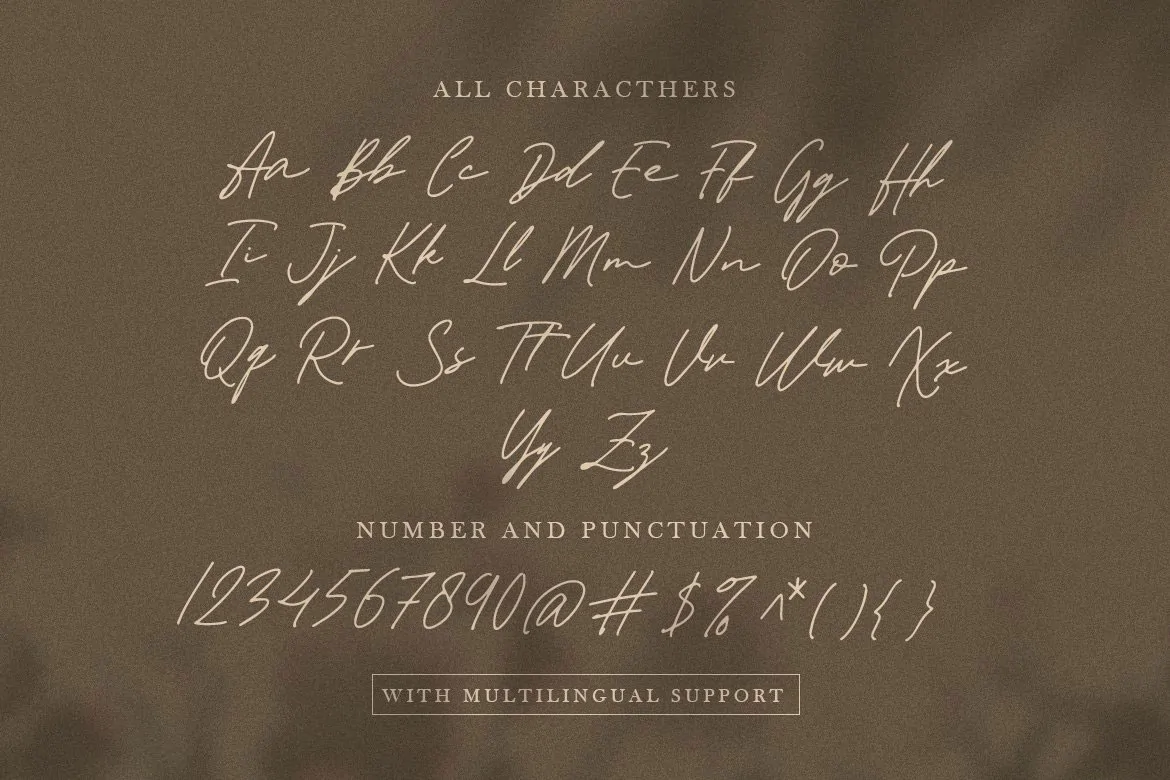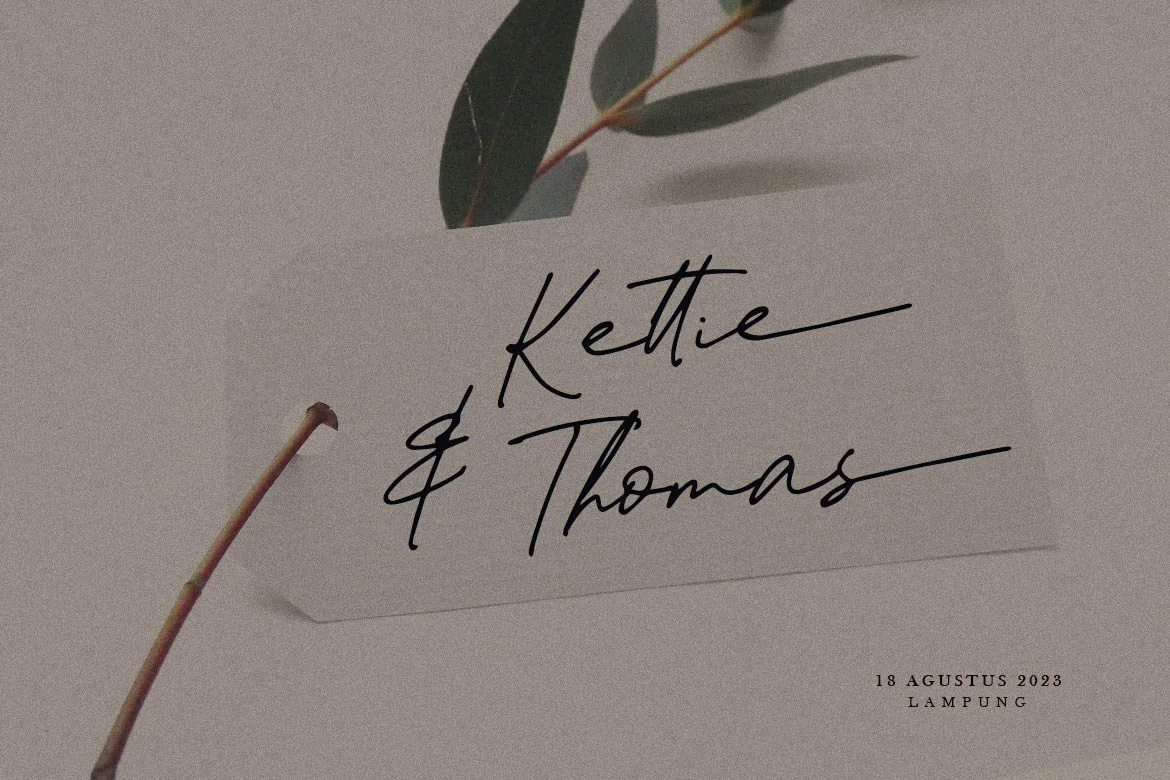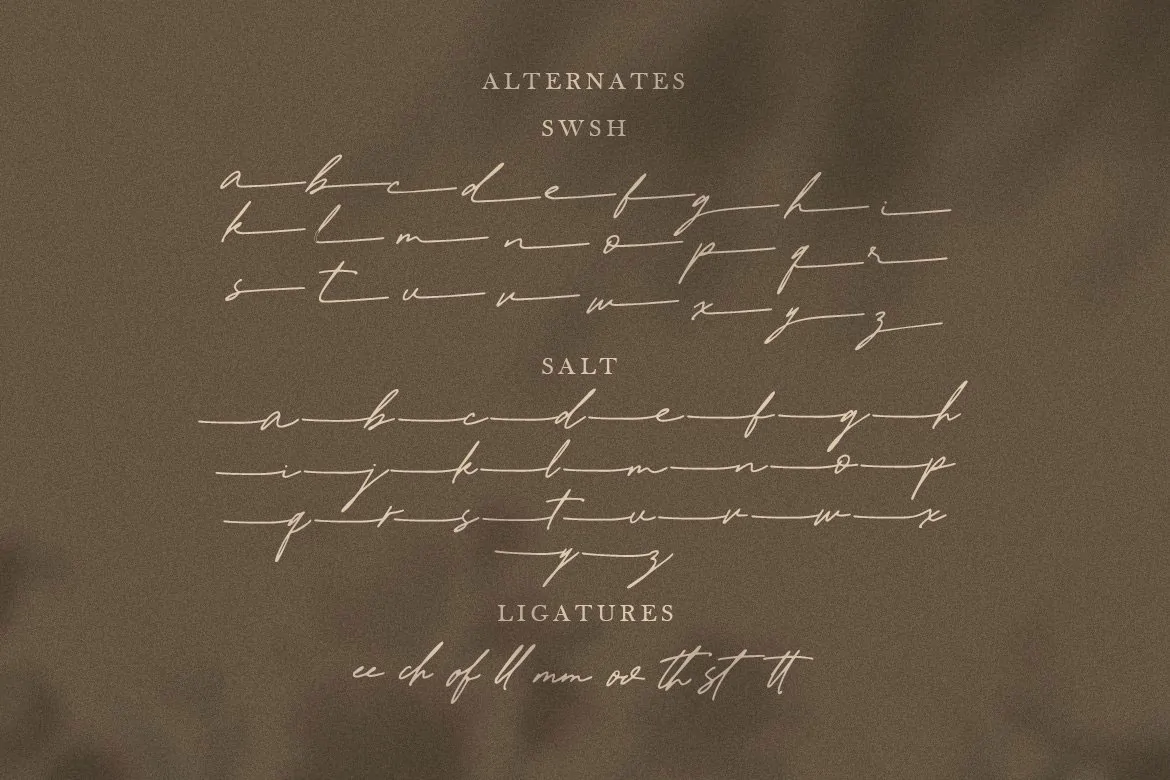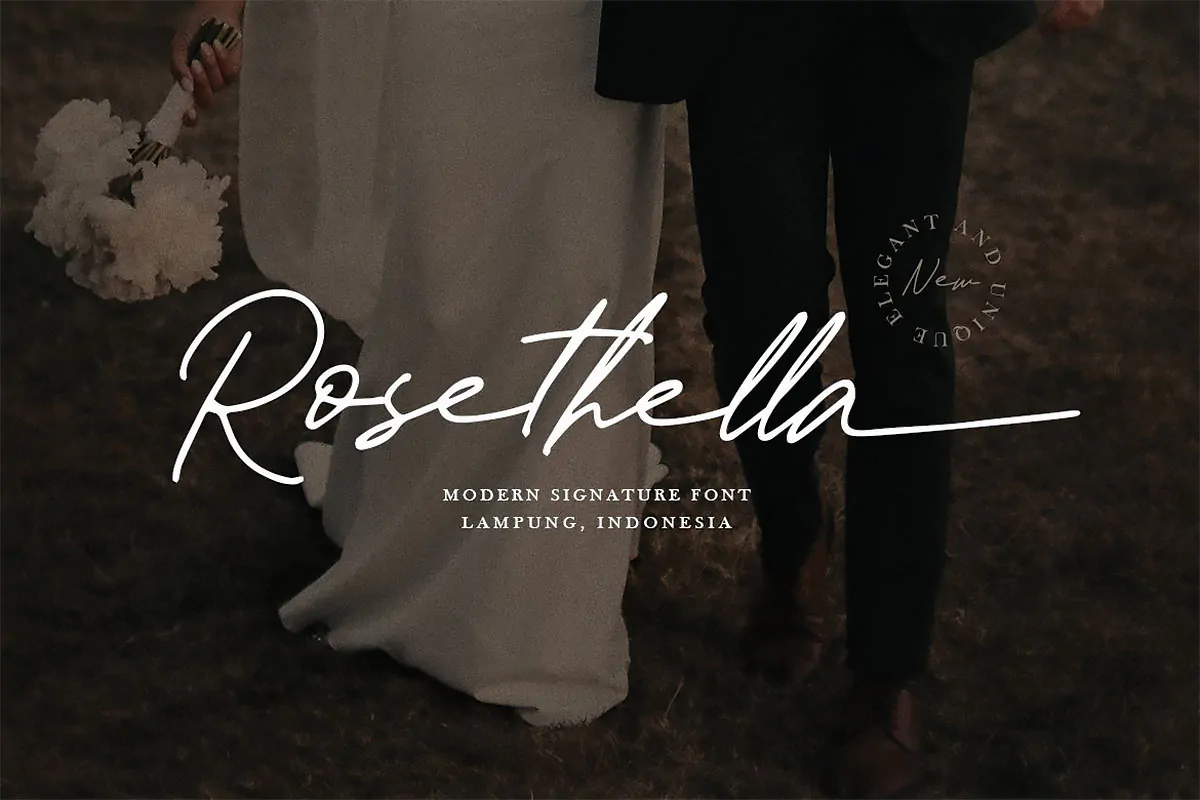
فونت سرهم نویسی امضایی مدرن Rosethella
فونت سرهم نویسی امضایی
فونت سرهم نویسی امضایی مدرن Rosethella یک قلم اسکریپت انگلیسی فوق العاده زیبا است که مناسب برای استفاده در طرحهای مختلف میباشد. این فونت زیبا با وزن معمولی طراحی شده است که میتوانید از آن در طراحی کارت ویزیت، پوستر، کاور آلبوم موسیقی، لوازم التحریر، آرایشی و بهداشتی، اینستاگرام، بسته بندی محصولات و … استفاده کنید.